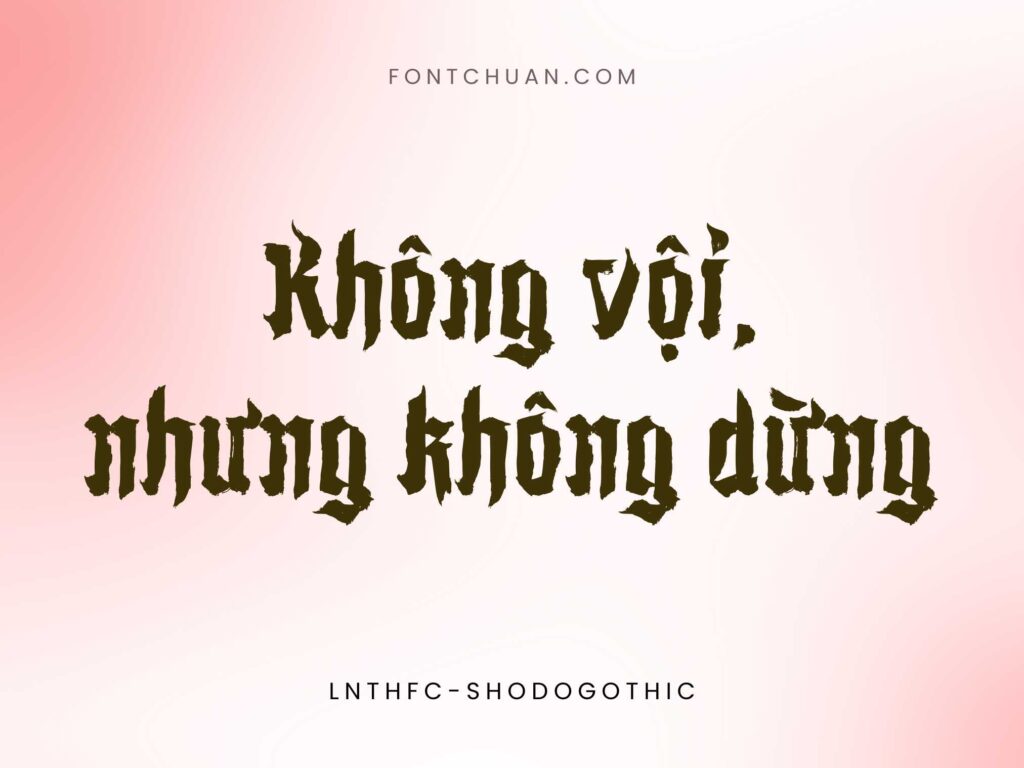
Font LNTH Shodo Gothic Việt Hóa
Tác giả Font: Mirco Zett
Shodo Gothic là một Font chữ Gothic mang phong cách kết hợp giữa thư pháp Á Đông và kiểu chữ trang trí phương Tây. Với các đường nét mạnh mẽ nhưng uyển chuyển, phông chữ này mang đến cảm giác huyền bí và nghệ thuật, phù hợp cho các thiết kế cần sự cá tính và ấn tượng. Nhờ vào vẻ đẹp vừa cổ điển vừa bí ẩn, Shodo Gothic cũng được xem là một Font chữ Halloween lý tưởng, thường được sử dụng trong các thiết kế mang chủ đề huyền bí, rùng rợn hoặc lễ hội. Phiên bản Việt hóa của LNTH giúp Shodo Gothic hỗ trợ đầy đủ các ký tự tiếng Việt, mang lại sự linh hoạt khi ứng dụng vào các dự án đa ngôn ngữ. Phông chữ này đã được sưu tầm và đăng tải bởi thành viên của Font Chuẩn nhằm đáp ứng nhu cầu đa dạng của cộng đồng thiết kế.
Về đặc điểm thiết kế, Shodo Gothic sở hữu các ký tự có nét bút phóng khoáng, kết hợp giữa sự sắc sảo của các đường nét chữ phương Tây và sự mềm mại của thư pháp châu Á. Phông chữ này đặc biệt phù hợp cho các dự án như thiết kế poster, bìa sách, logo, tiêu đề, và các ấn phẩm quảng cáo cần sự độc đáo và thu hút. Ngoài ra, Shodo Gothic cũng thích hợp cho các sự kiện như lễ hội, Halloween, và Trung thu, mang lại cảm giác bí ẩn và nghệ thuật. Trong lĩnh vực ngành nghề, phông chữ này được ứng dụng rộng rãi trong quảng cáo, thiết kế thiệp cưới, giáo dục và công nghệ, góp phần tạo nên phong cách riêng biệt và ấn tượng cho các sản phẩm và thương hiệu.